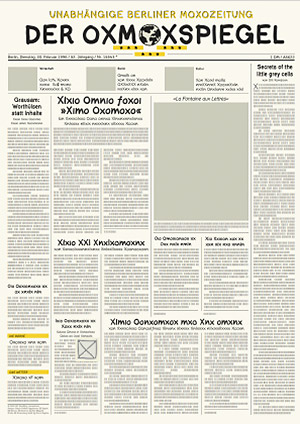
Fontcard-Serie: typografische Miniaturen, die Neuerscheinungen der
exklusiven FontFont-Bibliothek begleiteten. Wegen ihrer geringen Auflage wurden
die Fontcards rasch zum Sammelobjekt. Bis Ende 1997 erschienen 100 Motive. Zum
10-jährigen Jubiläum veröffentlicht Fontblog jetzt die
schönsten Fontcards als PDF-Edition: aufwendig restauriert, in
![]() Unsere Serie beginnen mit einer Fontcard aus dem Jahr 1996. Sie zeigt die
Schriftfamilie FF Layout von Gert Wippich –
die radikalste Typo-Provokation seit Gutenberg, denn die Layout-Font-Sippe macht
jeden Text unleserlich. Für Zeitungs- und Zeitschriftengestalter ist sie
allerdings ein Segen. Damit diese sich beim Layouten mit Blindtextmaterial nicht
vom Inhalt ablenken lassen, wandelt beispielsweise der Schnitt FF Oxmox
die 26 Buchstaben unseres Alphabets in sinnlose Letter-Kombination wie
»Oximoxiioxmo xionom Moxixo ...« um. Noch ein Zacken radikaler ist
FF Tramline: sie transformiert lebende Textzeilen in nichts sagende
Balken. Einzig die in 4 Schnitten verfügbare FF Layout, eine flotte
Handschrift, ist in der Lage, lesbare Texte darzustellen.
Zur Demonstration der FF-Layout-Power ließ FontFont-Herausgeber FSI FontShop International am Tag ihres Erscheinens (20. Februar 1996) den Berliner Tagesspiegel aus FF Layout nachbauen. Damals erstrahlte das Hauptstadt-Blatt gerade im neuen Layout von Mario Garcia, mit der Schmuckfarbe Gelb statt Rot – ein Novum in der internationalen Zeitungslandschaft. Der spätere Chefredakteur Giovanni di Lorenzo führte drei Jahre später bei seinem Amtsantritt wieder das alt-vertraute Rot ein.